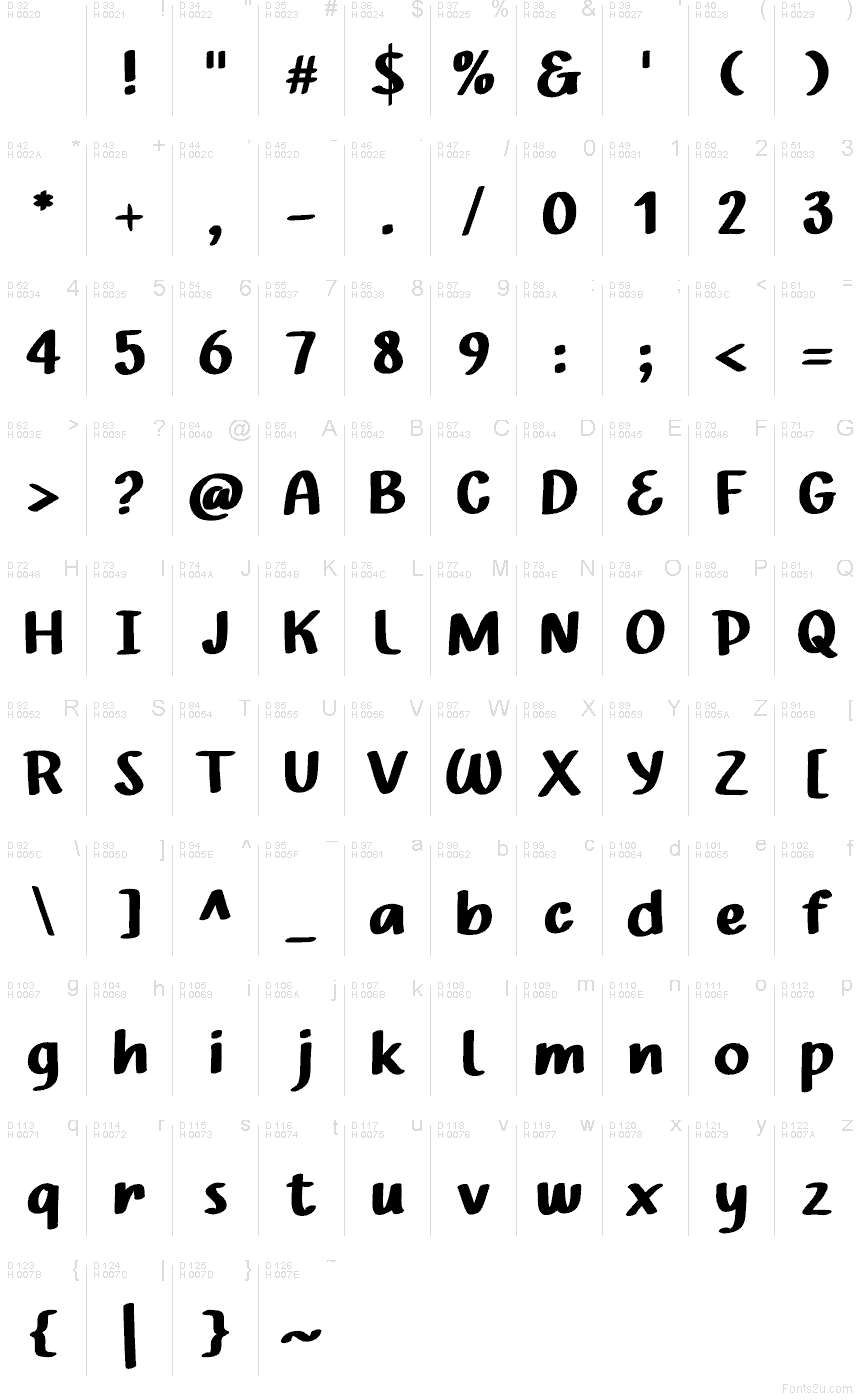
Great Cartoon
Great Cartoon від Hello Good Studio — це безкоштовний рукописний шрифт із широкими, заокругленими штрихами та легким, невимушеним ритмом кисті. Літери мають м'які вигини, дещо нерівні краї та приємну динаміку, завдяки чому шрифт не виглядає застиглим.
Great Cartoon чудово підходить для обкладинок дитячих книг, плакатів, логотипів, пакування товарів та графіки для соцмереж, адже його неформальний стиль виглядає як зроблений вручну, не втрачаючи при цьому форми. Він також ідеально пасує для листівок, наклейок та коротких заголовків, де теплий, енергійний стиль письма допомагає зробити дизайн більш особистим.